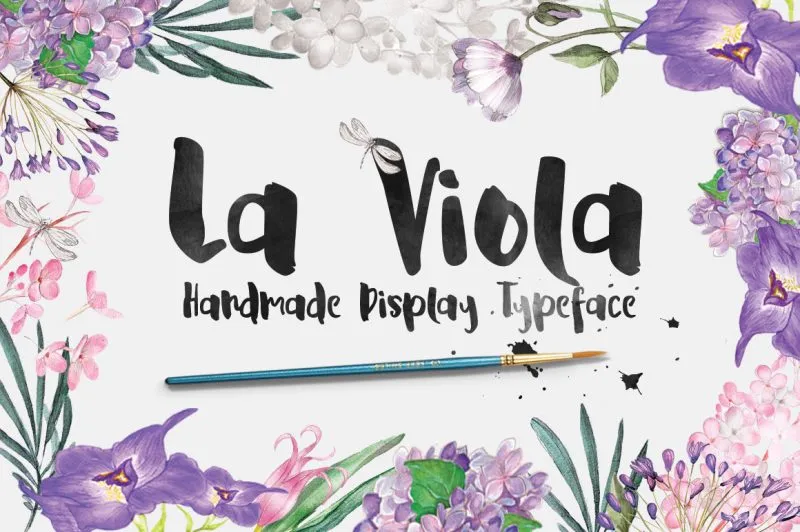
A La Viola Font é uma elegante fonte brush que traz estilo e personalidade a qualquer texto que você insere. Inspirada no trabalho dos artistas grafistas contemporâneos, ela combina linhas distintas com detalhes delicados, criando um visual único e atemporal. Seu designer, Hamilton, tem um talento notável em criar fontes que não só destacam a escrita, mas também expressam sua essência única através de cada caractere. Essa fonte é especialmente adequada para elementos visuais de blogs de design gráfico ou websites de arte digital. Suas linhas suaves e detalhes incisivos ajudarão você a transmitir seu mensageiro de forma atraente e impactante. Mesmo sendo uma fonte brush, La Viola mantém um equilíbrio perfeito entre levedade e força, o que é especialmente útil para textos em grande tamanho ou elementos visuais de alto contraste. Acreditamos que você encontrará este produto tão atraente quanto revolucionário, capaz de transformar qualquer página onde for inserida. Experimente La Viola Font hoje e veja como ela pode se destacar no seu próximo projeto gráfico. Você não vai desapontado!